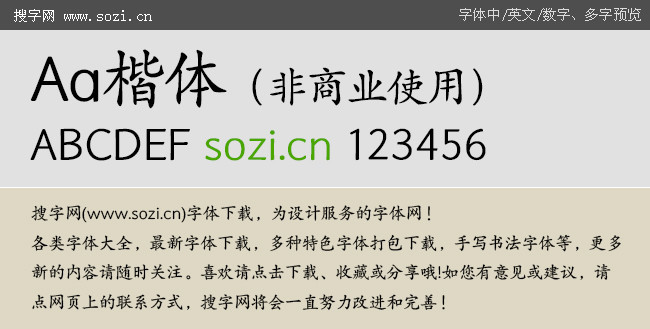
Aa楷體(非商業(yè)使用)
搜字網(wǎng)給大家提供一款A(yù)a楷體(非商業(yè)使用)中文字體下載,該字體字形端正,簡潔大方,整體效果出色,適合海報(bào)設(shè)計(jì)、包裝畫冊等宣傳廣告等應(yīng)用(此字體為個(gè)人非商用版,商用可以聯(lián)系QQ:1006760504)。